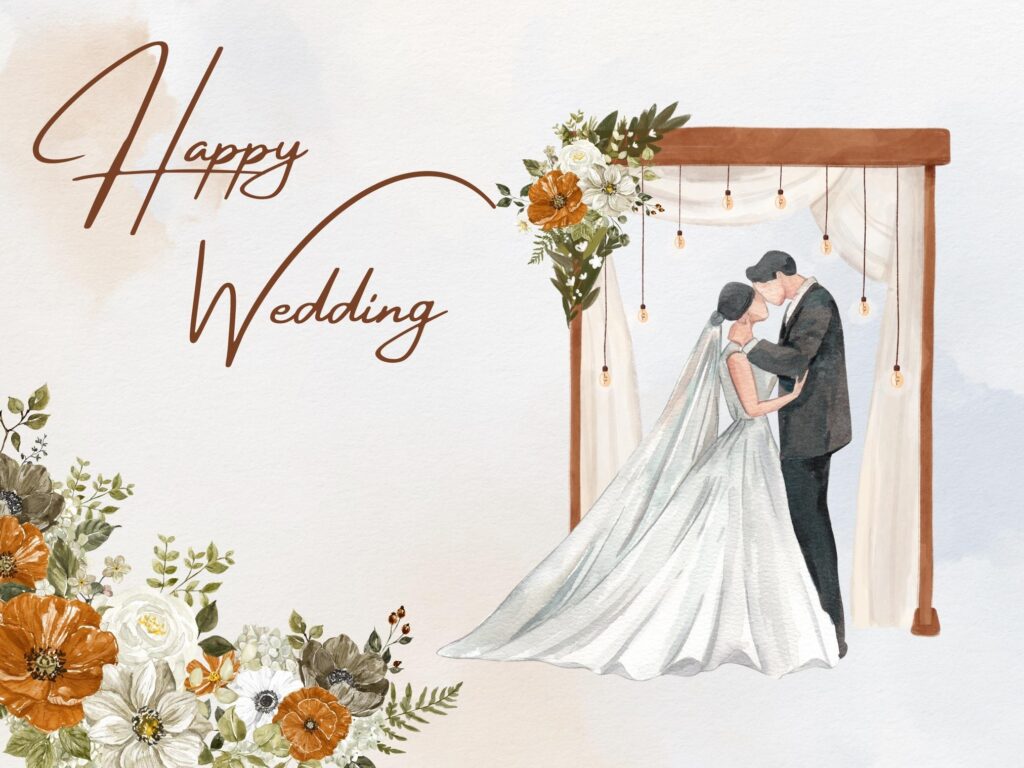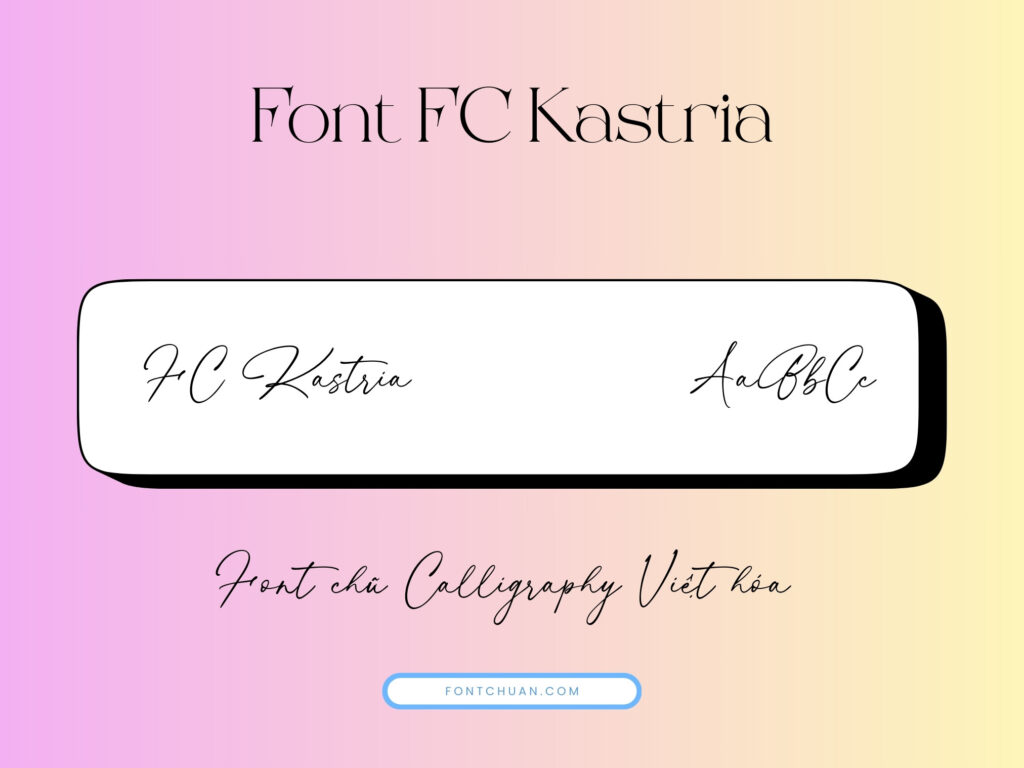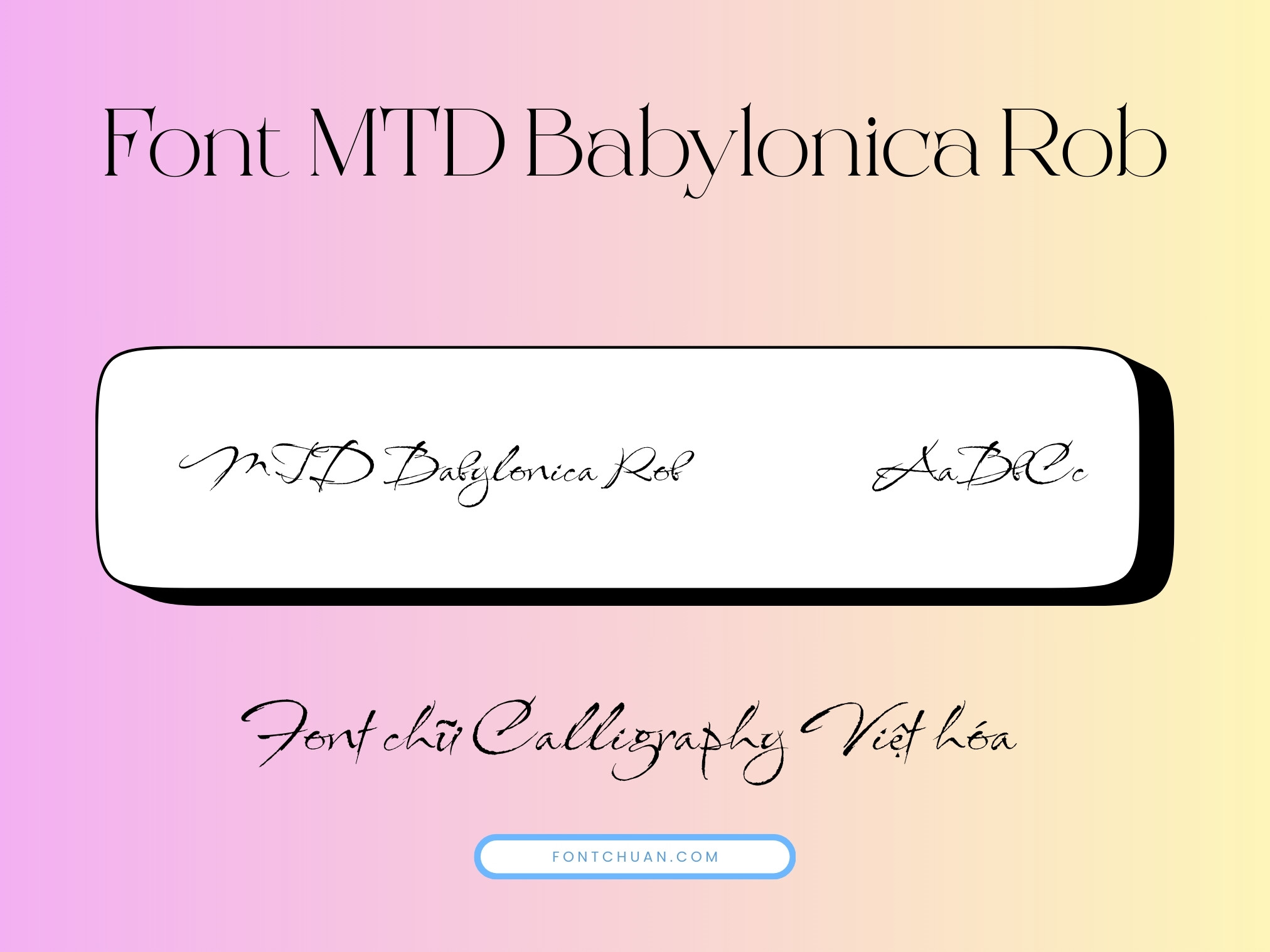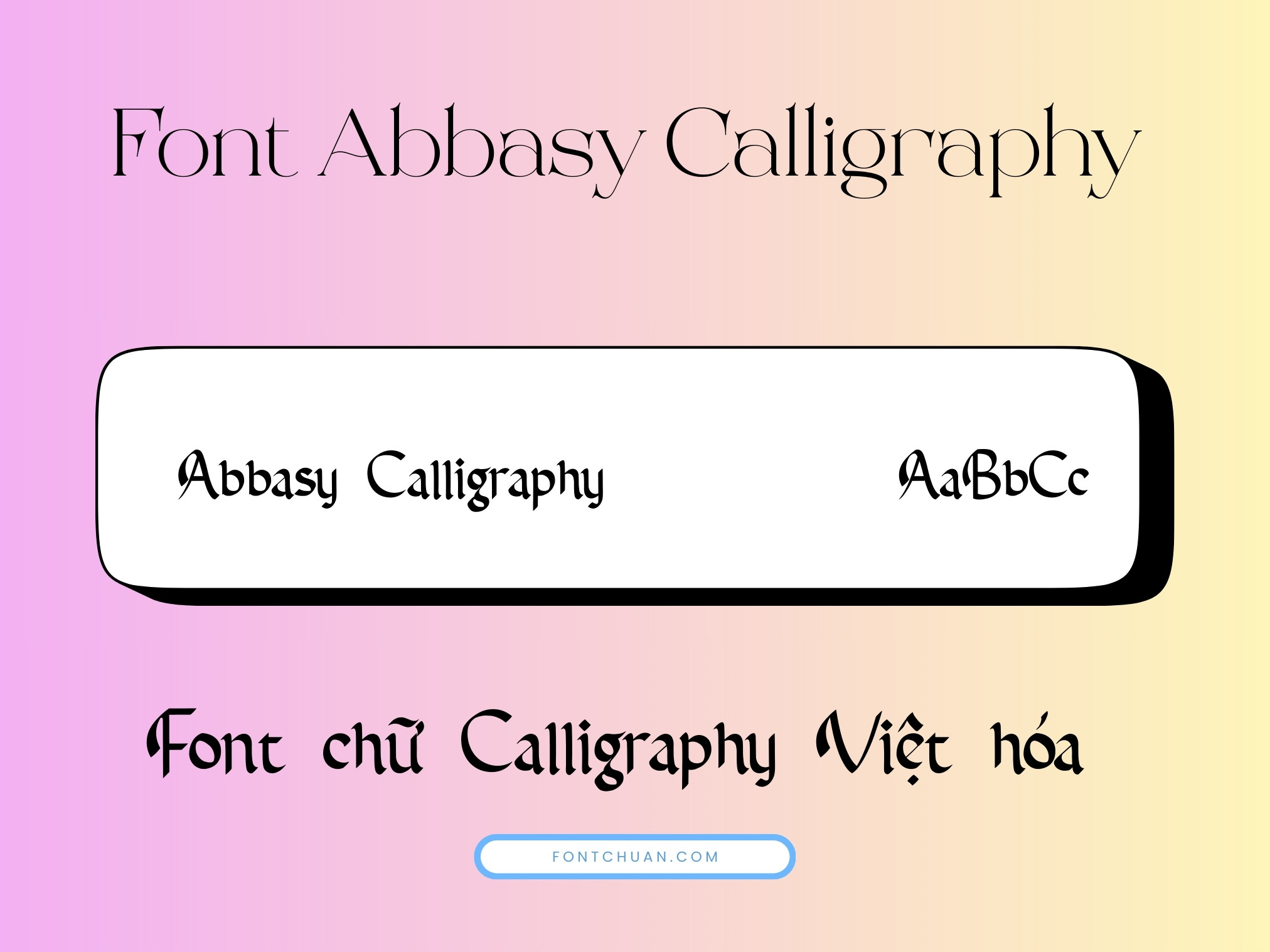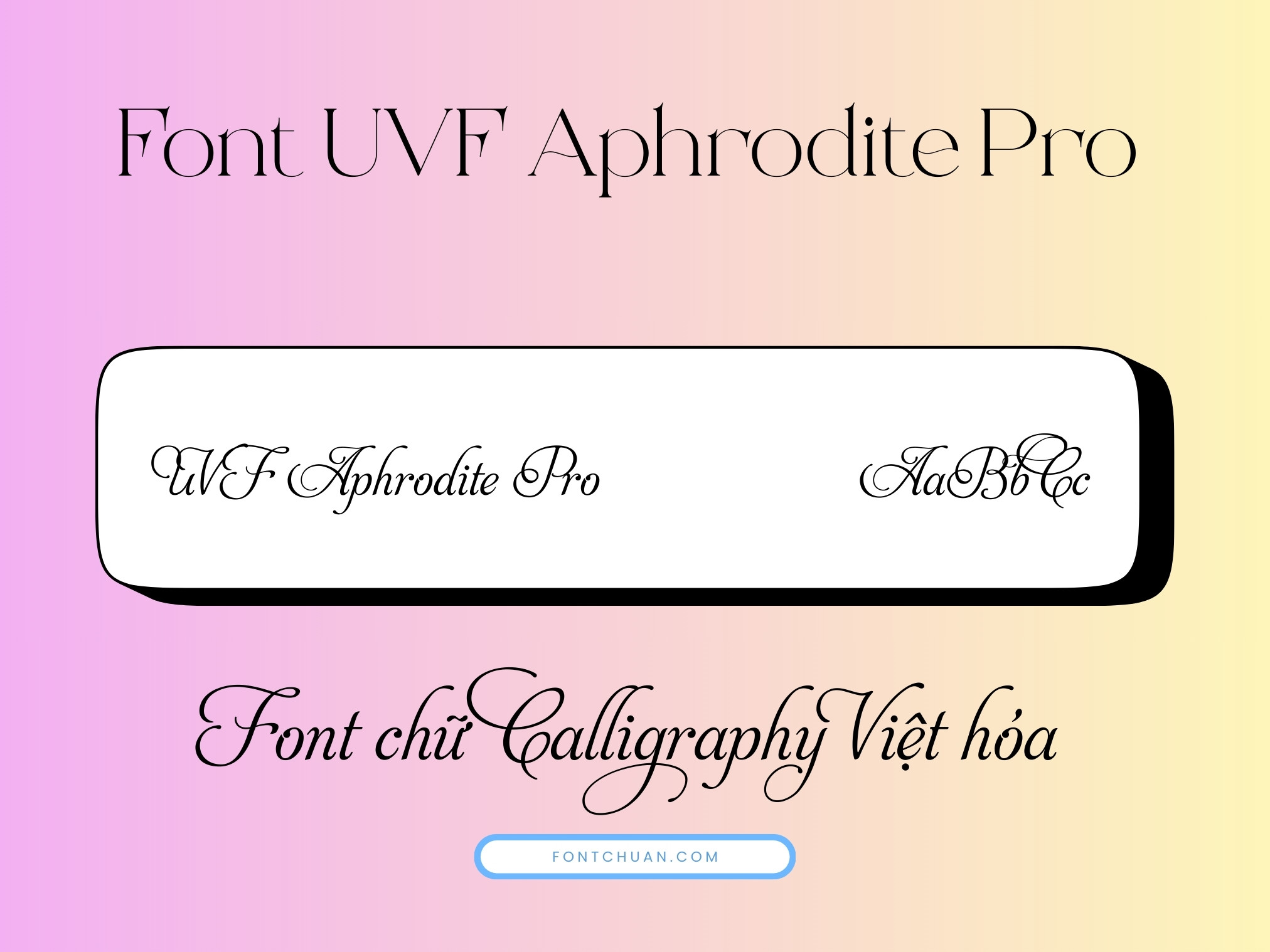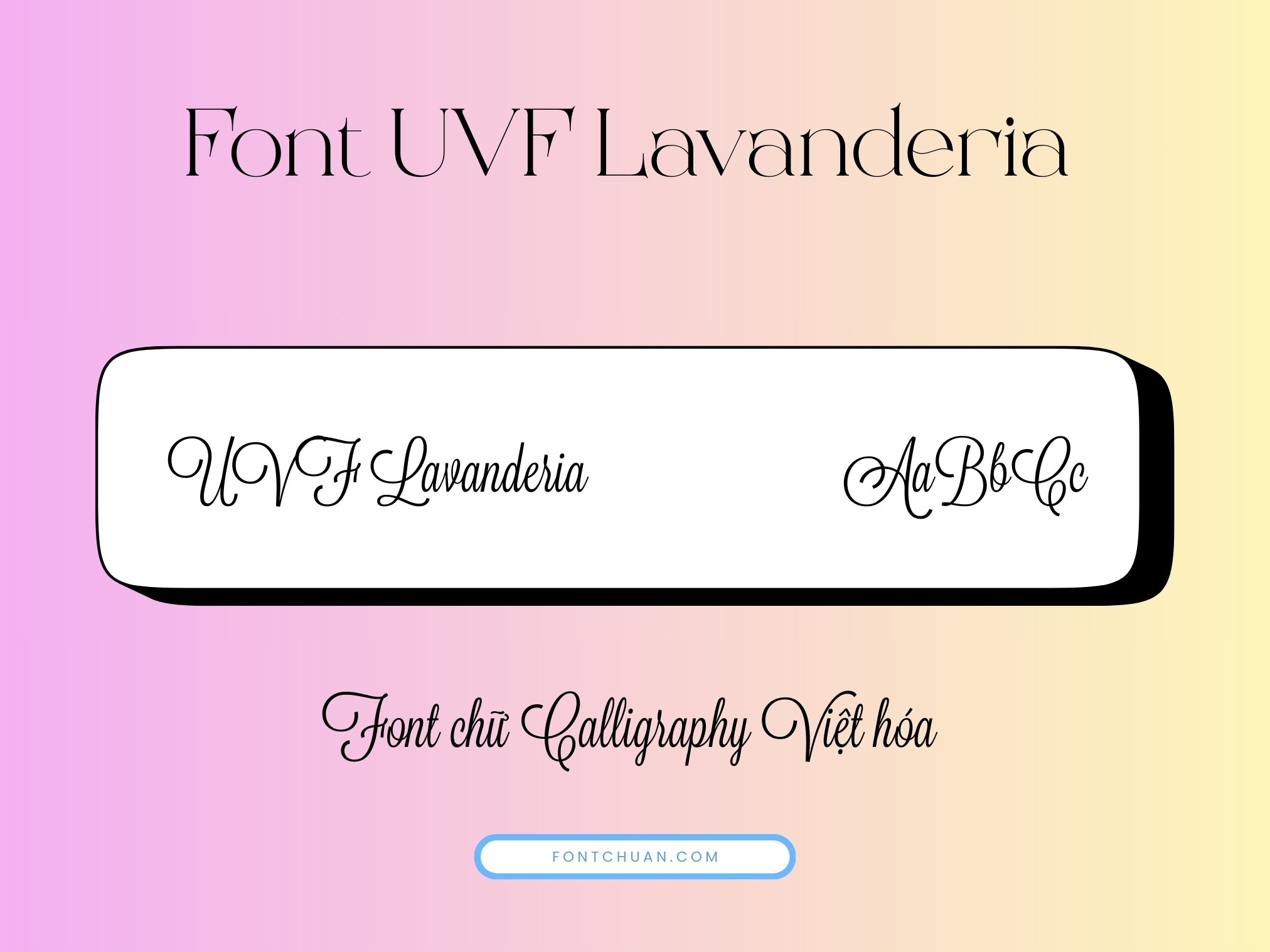
Tải bộ Font chữ Calligraphy Việt hóa đẹp nhất và miễn phí
Font calligraphy Việt hóa là những phông chữ thư pháp Latin đã được bổ sung đầy đủ dấu và ký tự tiếng Việt, mang phong cách chữ viết tay nghệ thuật (script font) với nét bút uốn lượn mềm mại như viết bằng bút lông (brush font). Trong lĩnh vực thiết kế, các font chữ này nổi tiếng vì vẻ đẹp lộng lẫy và sang trọng mà chúng đem lại cho thiết kế đồ họa. Hãy cùng khám phá để lựa chọn font chữ ấn tượng cho thiết kế thương hiệu và dự án sáng tạo của bạn.
Font calligraphy Việt hóa là gì?
Font calligraphy là nhóm kiểu chữ lấy cảm hứng từ Font thư pháp nghệ thuật, nổi bật với những nét bút mềm mại, đường cong uốn lượn tinh tế và giàu tính nghệ thuật. Đây là phong cách chữ thường được tạo ra bằng ngòi bút chuyên dụng, mang đến cảm giác thanh lịch, sang trọng và đầy cảm xúc.
Phiên bản Việt hóa của font calligraphy là khi nhà thiết kế mở rộng bảng mã ký tự để hỗ trợ Unicode tiếng Việt, bao gồm đầy đủ các chữ cái có dấu như ă, â, ê, ô, ơ, ư, đ cùng các dấu thanh (sắc, huyền, hỏi, ngã, nặng). Việc này đảm bảo chữ không bị lỗi hiển thị hoặc mất dấu khi sử dụng trong các dự án thiết kế dành cho người dùng Việt Nam.
Trong lĩnh vực typography, font calligraphy Việt hóa thường được ứng dụng trong:
• Thiệp cưới và thiệp mời sự kiện sang trọng.
• Thiết kế logo cho thương hiệu cao cấp hoặc cửa hàng boutique.
• Ấn phẩm truyền thông như poster, social media post, hoặc banner quảng cáo.
Các nền tảng thiết kế trực tuyến như Canva hay Figma cũng cho phép tích hợp font calligraphy Việt hóa, giúp nhà thiết kế dễ dàng tạo sản phẩm đồng nhất từ online đến in ấn.
Ưu điểm khi dùng font Calligraphy Việt hóa
Hỗ trợ đầy đủ tiếng Việt
Các font calligraphy Việt hóa được bổ sung đủ ký tự tiếng Việt, giúp tránh tình trạng lỗi mất dấu hoặc dấu chồng. Điều này đặc biệt quan trọng khi thiết kế nội dung dài hoặc văn bản mang tính trang trọng, đảm bảo tính chuyên nghiệp và khả năng đọc mạch lạc.
Giữ nguyên nét nghệ thuật
Khi Việt hóa, nhà thiết kế vẫn bảo toàn các yếu tố nghệ thuật như ligature (chữ ghép), alternate (chữ thay thế) và swash (nét vẽ trang trí). Điều này giữ trọn phong cách và “cá tính” nguyên bản của font, tránh mất đi sức hút thị giác vốn có.
Đa dạng ứng dụng
Font calligraphy Việt hóa linh hoạt trong nhiều lĩnh vực:
• Thiệp mời và poster sự kiện.
• Social post tạo cảm xúc ấn tượng.
• Bao bì sản phẩm cần sự tinh tế.
• Logo boutique hay thương hiệu cá nhân mang tính thủ công, nghệ thuật.
Tính cá nhân hóa cao
Nhờ vào đặc điểm mềm mại và sáng tạo, font calligraphy Việt hóa giúp thiết kế truyền tải cá tính riêng của người làm. Từ đó, mỗi dự án trở nên độc đáo, ghi dấu ấn với người xem và tạo cảm giác gần gũi, ấm áp.
Giới thiệu top 8+ Font chữ Calligraphy việt hóa đẹp nhất hiện nay
Font Calligraphy Việt hóa FC Handstand
FC Handstand Việt Hóa – font viết tay của Areatype Studio kết hợp nét brush hiện đại và thư pháp, mang lại cảm giác mạnh mẽ, tự nhiên. Phiên bản Việt hóa do Font Chuẩn chia sẻ miễn phí, hỗ trợ đầy đủ tiếng Việt, phù hợp cho thiết kế thời trang, poster, quảng cáo và các dự án thương hiệu cá tính.
Font chữ Calligraphy Việt hóa FC Kastria
FC Kastria Việt Hóa – font chữ ký tay vintage của Muhamad Yusron Billah với nét mềm mại, thanh lịch. Phiên bản Việt hóa do Font Chuẩn chia sẻ miễn phí, lý tưởng cho thiết kế ngành làm đẹp, thiệp cưới, spa, poster và truyền thông xã hội.
Font FC Opulent Brush Việt Hóa
FC Opulent Brush Việt Hóa – font script viết tay hiện đại của Sam Parrett (2018), mang nét thư pháp sáng tạo và nghệ thuật. Việt hóa bởi Font Chuẩn với đầy đủ ký tự tiếng Việt, phù hợp cho thiệp mời, ấn phẩm Tết, sự kiện, quảng cáo, spa và ẩm thực.
Font MTD Babylonica Rob Việt Hóa
MTD Babylonica Rob Việt Hóa – font thư pháp mềm mại của Typesetit, Việt hóa bởi Mộc Hạ, hỗ trợ đầy đủ tiếng Việt và hơn 200 ngôn ngữ. Lý tưởng cho thiệp cưới, thương hiệu cao cấp, typography nghệ thuật, quảng cáo và sự kiện.
Font Abbasy Calligraphy Việt hóa
Abbasy Calligraphy Typeface Việt Hóa – font thư pháp tinh tế pha chút hiện đại, hỗ trợ đầy đủ tiếng Việt. Lý tưởng cho thiệp mời, biển hiệu, ấn phẩm in ấn và các thiết kế mang tính nghệ thuật cao.
Font Calligraphy Việt hóa UVF Aphrodite Pro
UVF Aphrodite Pro Việt Hóa – font calligraphy sang trọng, kết hợp nét cổ điển và hiện đại, hỗ trợ đầy đủ tiếng Việt. Phù hợp cho logo, thiệp mời, bao bì, thương hiệu thời trang, mỹ phẩm và các thiết kế mang phong cách lãng mạn.
Font chữ Calligraphy Việt hóa UVF Lavanderia
UVF Lavanderia Việt Hóa – font calligraphy mềm mại, cảm hứng từ biển hiệu cổ San Francisco, hỗ trợ đầy đủ tiếng Việt. Hoàn hảo cho thiệp cưới, logo, branding, thiết kế thời trang và các ấn phẩm cần sự tinh tế, lãng mạn.